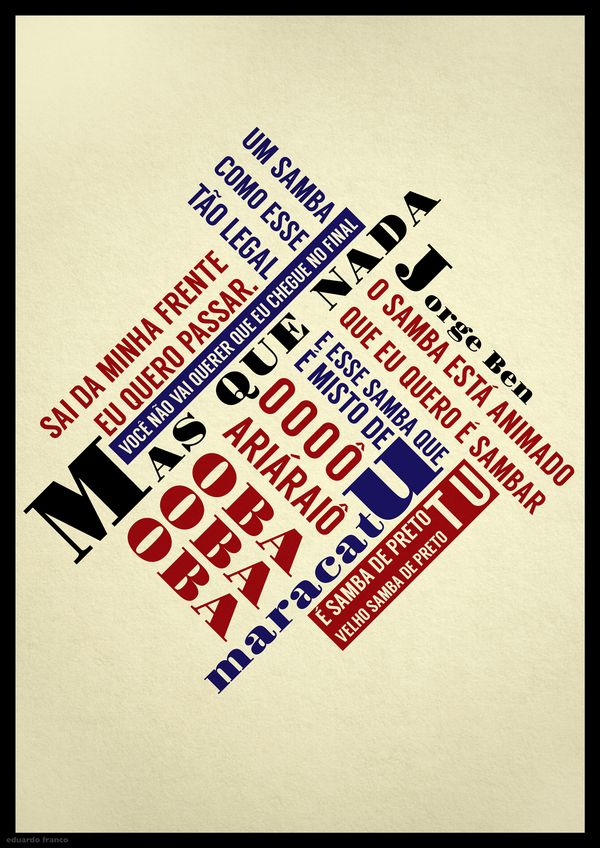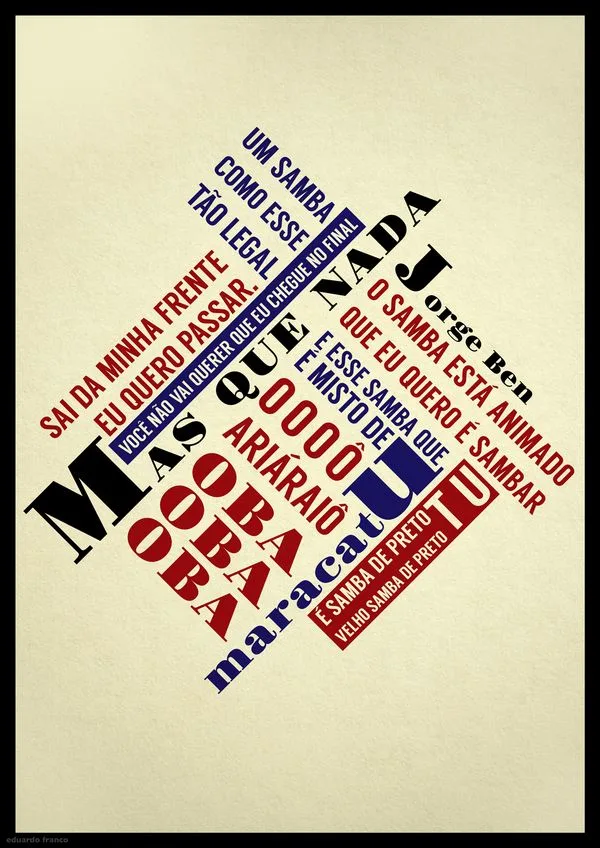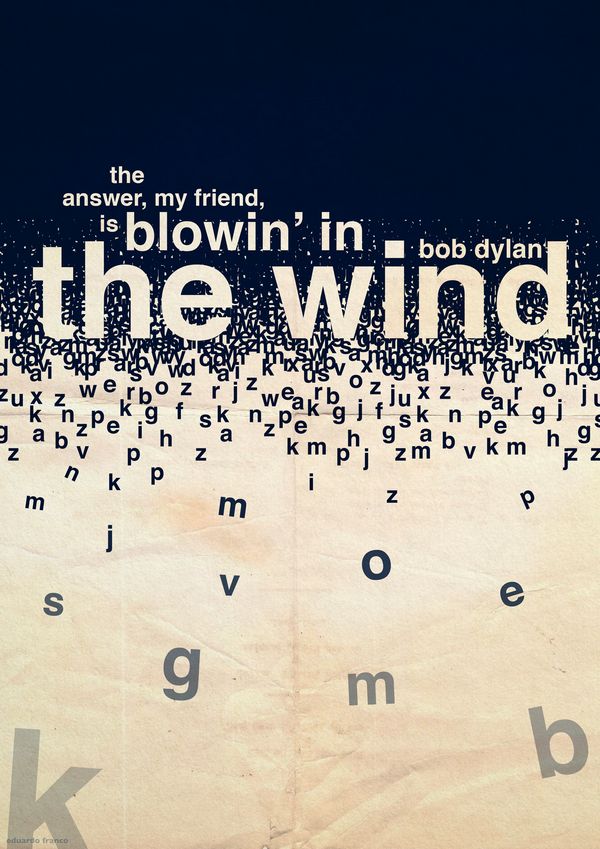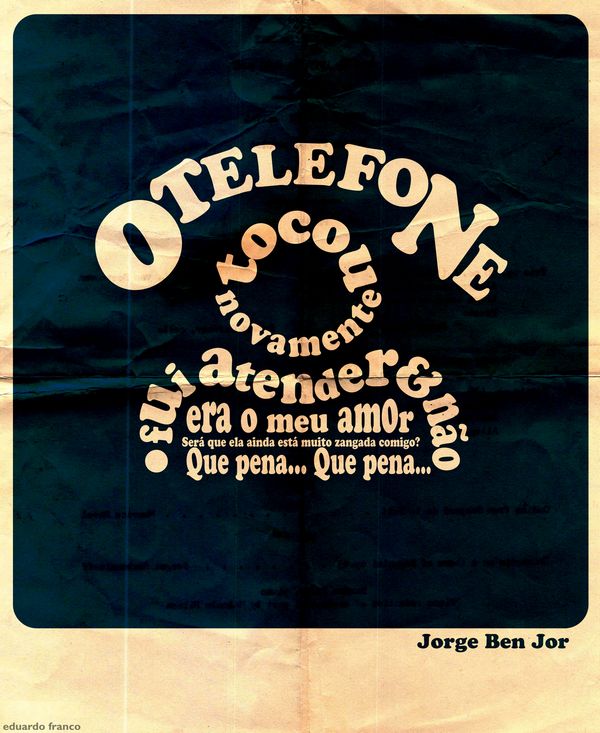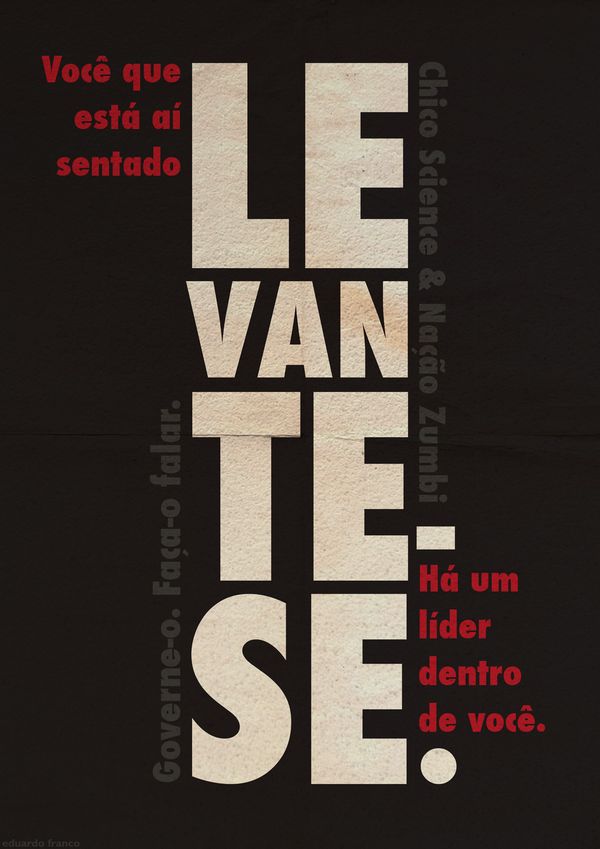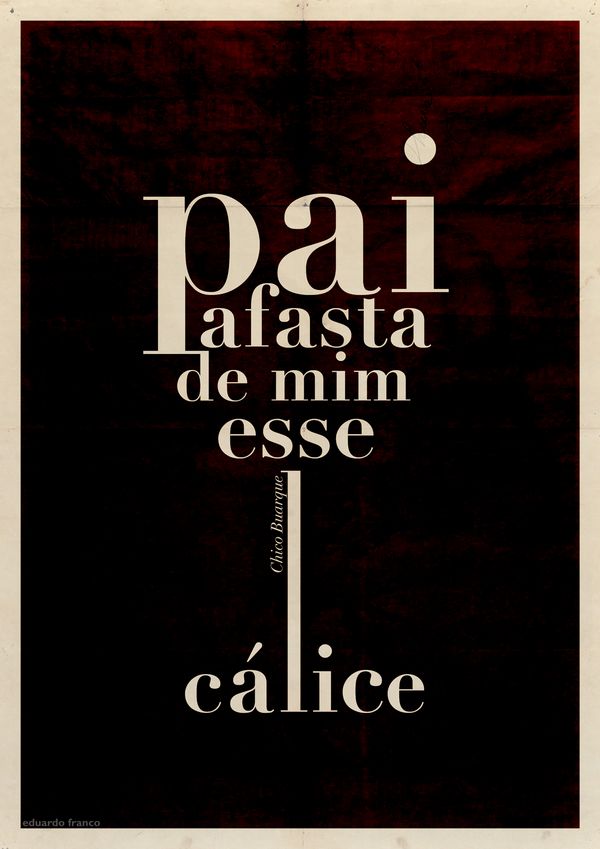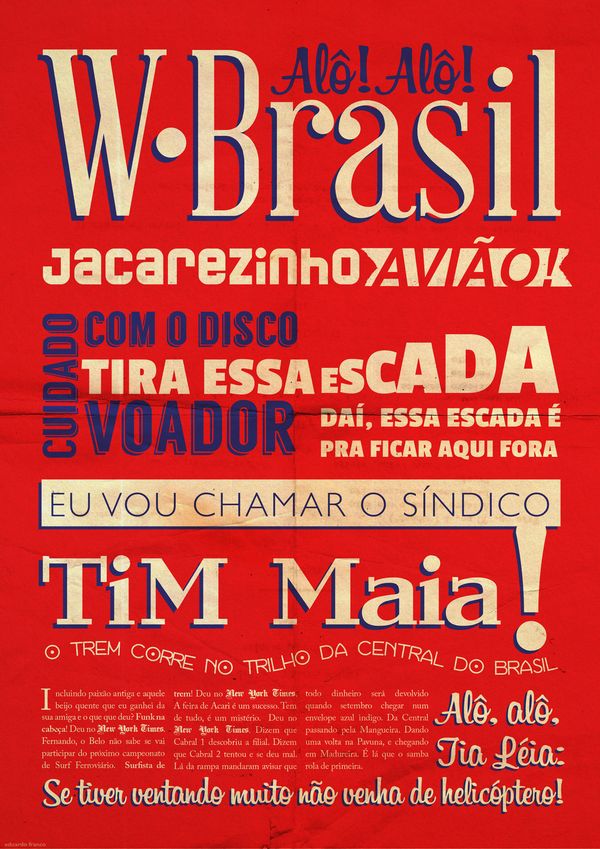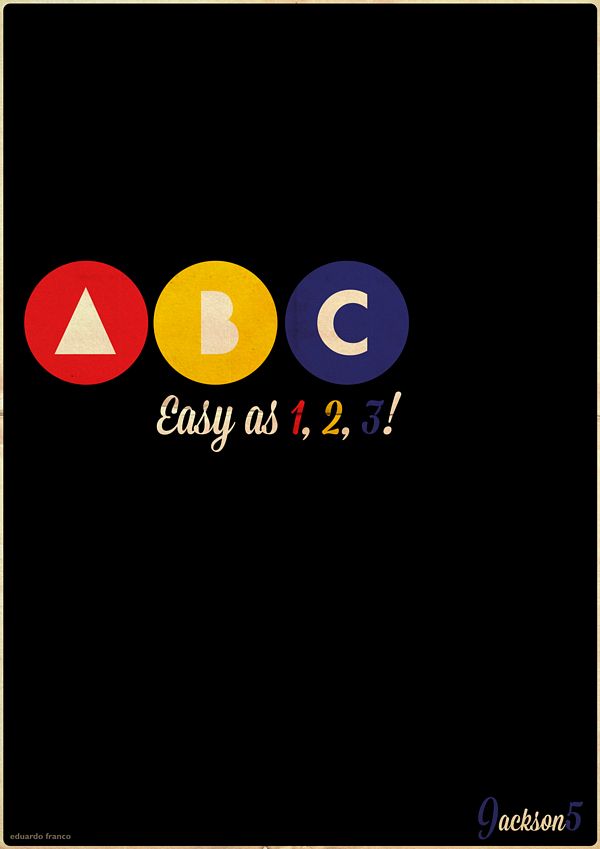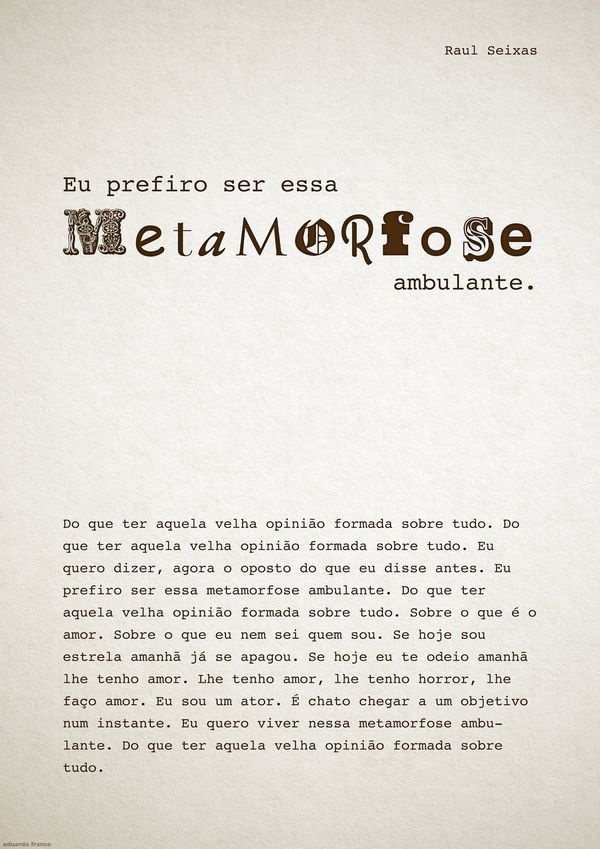
Pôsteres com a tipografia relacionada as músicas famosas
Pra quem gosta de música; e música de qualidade… olha que interessante o trabalho do designer Eduardo Franco, que criou vários cartazes musicais…quer saber como???
Ele usa a Tipografia para trazer novos sentidos artísticos ás músicas!!
O objetivo do designer é mostrar o uso da tipografia como ferramenta de representação gráfica e comunicação visual.
Seus cartazes estão no tumblr Cartazes Tipográficos Musicais, onde ele publica um cartaz por dia e em cada dia usa musicas variadas, ele usa musicas de cantores brasileiros, à exemplo: Jorge Benjor e Chico Buarque e também sucessos estrangeiros como Wonder e Bob Dylan, Nação Zumbi, entre outros.
Vale apena conferir, veja abaixo alguns de seus cartazes…